Stellen Sie sich vor, Sie enthüllen bei jedem Klick eine visuelle Erzählung. Es ist die subtile Kunstfertigkeit hinter der Airbnb-Schriftart, die Sie möglicherweise nicht bewusst wahrnehmen, aber sie prägt Ihre gesamte Erfahrung mit der Plattform.
Schriftarten tragen die Stimme einer Marke, und als Webdesigner verstehe ich, wie eine Schriftart wie Airbnbs Cereal sowohl ein stiller Gesprächspartner als auch ein Lautsprecher für die Markenidentität sein kann.
Dieser Artikel enthüllt die Geschichte des ungesungenen Helden der Typografie im digitalen Bereich von Airbnb. Wir werden die Stränge der serifenlosen Schriftart erkunden und untersuchen, wie sie das Benutzererlebnisdesign und die visuelle Identität der Marke verbessert.
Am Ende der Reise werden Sie verstehen, wie diese scheinbar kleine Wahl monumental für die digitale Typografie sein kann.
Tauchen Sie ein in die Rolle der richtigen Schriftart, von Branding bis zur nutzbaren responsiven Schriftart.
In den kommenden Abschnitten, von Konzepten zu Airbnb-Branding bis zur Feinheit der Schriftmerkmale, erzählen wir die Reise der typografischen Entscheidungen von Airbnb und warum diese für Sie von Bedeutung sein könnten.
Welche Schriftart verwendet Airbnb?
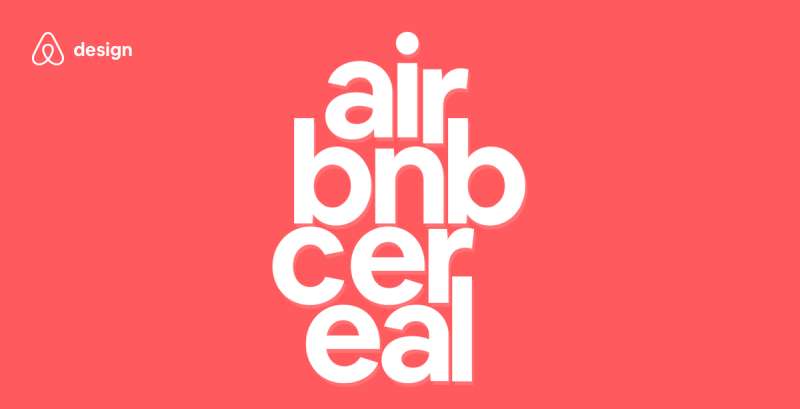
Ah, die perfekte Schüssel ‚Cereal‘. Diese freundliche, unauffällige Schriftart ist das, wovon Airbnb begeistert ist und was sie mit ganzem Herzen angenommen haben. Es ist die Schrift, die Sie sehen, egal ob Sie eine gemütliche Hütte im Wald oder ein schickes Stadtapartment buchen.
Es ist diese geometrische serifenlose Schriftart, die der Airbnb-Plattform einen menschlichen Touch verleiht, und sie wurde so gestaltet, dass sie genauso einladend ist wie die auf der Seite gelisteten Häuser.
Entstehung von Cereal
Wer hat diese wunderschöne Schüssel Cereal kreiert? Es ist das Brainchild des hauseigenen Designteams von Airbnb, mit ein wenig Hilfe von ihren Freunden bei Dalton Maag, der in London ansässigen Schriftgießerei.
Die Zusammenarbeit hat eine Schriftart hervorgebracht, die sowohl modern als auch freundlich ist, genau wie die Marke von Airbnb. Einfache, saubere geometrische Formen sind die Bausteine, mit genau dem richtigen Hauch von Rundheit, um sie zugänglich zu machen.
Die Schönheit von Cereal
Die Cereal-Schriftart ist nicht nur ein hübsches Gesicht. Sie hat auch funktional einiges zu bieten. Sie kommt in sechs verschiedenen Gewichtsvarianten, wodurch sie ziemlich vielseitig ist.
Sie können sie nutzen, um hervorzuheben, zu flüstern, zu schreien – alles mit einer konsistenten Stimme. Und die Skalierbarkeit? Oh, sie meistert es wie ein Champion. Egal in welcher Größe, Cereal behält ihre Integrität.
Alternativen zur Airbnb-Schriftart
Wenn Cereal nicht ganz Ihr Fall ist oder Sie nach etwas anderem für Ihre eigene Marke suchen, keine Sorge. Es gibt ein Buffet an alternativen Schriften da draußen.
Roboto
Roboto ist wie der ältere, weisere Cousin von Cereal. Entwickelt von Google, ist es eine weitere geometrische serifenlose Schriftart, die sauber, modern und super adaptierbar ist. Sie hat eine noch größere Bandbreite an Gewichten und Stilen. Sie ist ziemlich populär und Sie haben sie wahrscheinlich schon gesehen.
Proxima Nova
Nächster im Menü ist Proxima Nova. Stellen Sie sich Cereal vor, aber mit etwas mehr Kante und weniger Rundheit. Sie ist professionell, aber nicht zu steif, freundlich, aber nicht übermäßig. Sie ist ein wunderbarer Mix, der in vielen Kontexten gut funktioniert.
Die Wirkung von Typografie auf Branding
Sie könnten denken, dass Schriftarten nur Schriftarten sind, aber in der Welt des Designs sind sie so viel mehr. Sie können die Identität einer Marke definieren und beeinflussen, wie Nutzer die Marke wahrnehmen.
Die Macht von Schriftarten
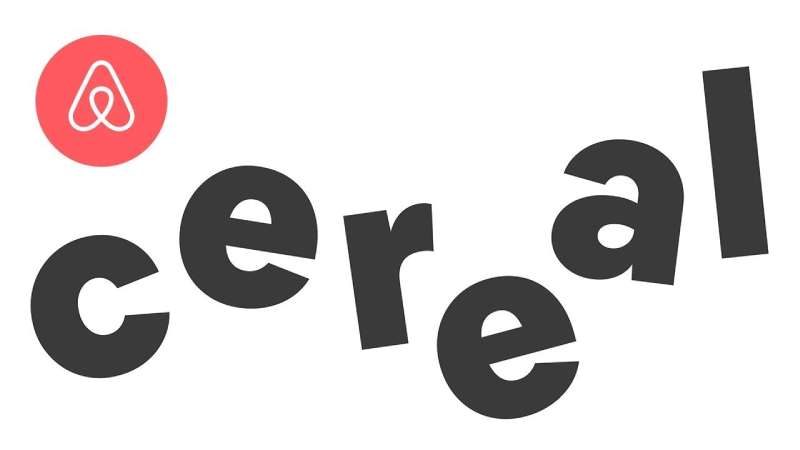
Schriftarten sind wie die Kleidung, die Worte tragen. Sie können Worte ernst, lässig, lustig oder raffiniert erscheinen lassen. Wenn eine Marke wie Airbnb eine Schriftart wählt, macht sie eine Aussage über ihre Identität. Und mit Cereal sagt Airbnb, dass es freundlich, modern und einladend ist.
Konsistenz ist der Schlüssel
So wie Sie kein nicht zusammenpassendes Outfit tragen würden, müssen Marken sicherstellen, dass ihre Typografie konsistent ist. Hierbei ist eine benutzerdefinierte Schriftart von Vorteil. Mit Cereal kann Airbnb sicherstellen, dass jedes Wort, das es spricht, konsistent mit seiner Marke ist, egal wo es erscheint.
FAQ zur Airbnb-Schriftart
Wie heißt die Airbnb-Schriftart?
Die Schrift, die die Airbnb-Seite in Eleganz hüllt? Sie heißt Cereal. Eine schicke, maßgeschneiderte serifenlose Schönheit. Sie sticht hervor, nicht wahr?
Maßgeschneidert, um Zuschauer mit ihrer einzigartigen visuellen Identität zu fesseln, verkörpert Cereal die Wärme und Gastfreundschaft, die Airbnb durch sein Branding vermitteln möchte.
Warum hat Airbnb eine benutzerdefinierte Schriftart erstellt?
Warum sich mit dem Von-der-Stange begnügen, wenn man maßgeschneidert gehen kann? Das hat sich auch Airbnb gedacht.
Die Erstellung von Cereal diente dazu, eine unverwechselbare visuelle Ausdrucksweise zu treffen; ein Schriftstil, der nahtlos mit der Typografie der Markenidentität resoniert und das Benutzererlebnisdesign mit jener heimeligen Atmosphäre verstärkt, die Airbnb liebt.
Kann ich die Airbnb-Schrift herunterladen?
Halten Sie die Pferde, mein Freund. Cereal ist nicht zu haben. Es ist Airbnbs eigenes Spielzeug, nicht für die öffentliche Nutzung lizenziert.
Respektieren Sie ihr geistiges Eigentum, finden Sie vielleicht Alternativen mit ähnlicher Lesbarkeit der Schriftart oder Stimmung, aber denken Sie daran, keine zwei Schriften tragen dieselbe Seele.
Wie beeinflusst die Airbnb-Schrift das Branding?
Schriftarten flüstern das Wesen einer Marke in Ihr Unterbewusstsein. Mit Cereal sprechen die Branding-Schriften von Airbnb in entspannten, aber raffinierten Tönen.
Es ist alles Teil ihres Corporate Branding-Werkzeugs – dafür zu sorgen, dass Sie bei jeder Online-Interaktion diese Airbnb-Umarmung spüren.
Ist die Airbnb-Schrift als zugänglich angesehen?
Zugänglichkeit ist der Schlüssel, und ja, Cereal erfüllt dieses Kriterium. Ihre klaren Formen und ausreichenden Abstände erhöhen die Lesbarkeit der Schriftart, sodass auch Personen mit Sehbeeinträchtigungen problemlos an der Airbnb-Party teilnehmen können. Es ist Benutzerfreundlichkeit, die in den Stoff der digitalen Typografie eingewoben ist.
Wie verbessert die Airbnb-Schrift das Benutzererlebnis?
Cereal wurde frisch gebacken, mit dem Design des Benutzererlebnisses im Sinn.
Ihr einheitliches Aussehen über digitale Plattformen hinweg bedeutet keine störenden Änderungen für die Augen – einfach reibungsloses Navigieren von Bildschirm zu Bildschirm, was die Usability der Plattform erhöht und die Stimme der Marke fest im Einklang hält.
Um welche Art von Schriftart handelt es sich bei der Airbnb-Schrift?
Cereal gehört zur Familie der serifenlosen Schriftarten – keine zusätzlichen Schnörkel an den Buchstaben. Schlank. Modern. Passt hervorragend zu digitalen Displays.
Eine bevorzugte Wahl für klare digitale Branding-Assets, halten serifenlose Schriften wie Cereal alles klar und zeitgemäß.
Ist die Airbnb-Schrift einzigartig für Airbnb?
Einzigartig wie Schneeflocken in ihrem Design, sind benutzerdefinierte Schriftarten wie Cereal seltene Vögel.
Die Schriftart von Airbnb mit ihrer deutlichen und unabhängigen Existenz ist nicht nur einzigartig – sie ist eine SEO-Einheit ihrer selbst innerhalb des Designsystems. Sie ist Airbnbs Unterschrift in typografischer Form.
Wie hat Airbnb sich für diesen speziellen Schriftstil entschieden?
Es war keine Würfelwurfentscheidung. Cereal auszuwählen, war durchdacht, strategisch. Man wollte etwas, was die Markenidentität widerspiegelt.
Eine Schrift, gezüchtet für Lesbarkeit, Flexibilität über Medien hinweg, etwas, das ‚Airbnb‘ sang, ohne ein Wort zu sagen. Es ist ein Game-Changer in der visuellen Identität.
Welche Art von Schrifttrends setzt die Airbnb-Schrift?
Airbnb hat mit Cereal etwas vor – sie setzt Typografietrends, indem sie Wärme mit Modernität verbindet. Sie beweist, dass benutzerdefinierte Schriftarten als Branding-Assets eine firmeneigene digitale Anwesenheit neu definieren können.
Beobachten Sie, wie mehr Marken auf diesen Designtrend-Zug aufspringen und ihre eigenen typografischen Signaturen suchen.
Fazit
Wir sind durch die Gassen der digitalen Typografie gewandert und haben die vielfältigen Geschichten aufgedeckt, die innerhalb der Airbnb-Schriftart verwoben sind. Cereal steht nicht nur als eine Serie wohlgestalteter Linien und Kurven, sondern als Leuchtfeuer der Markenidentität von Airbnb. Es ist klar.
- Die Serifenlosigkeit der Schrift strahlt nicht nur ästhetische Anziehungskraft aus; sie ist der Grundstein des Benutzererlebnis-Designs.
- Die bewusste Wahl dieser Schriftart spiegelt Airbnbs Philosophie wider – Einfachheit, Inklusivität und Wiedererkennung.
In jeder Hinsicht ist Cereal eine Schrift, die spricht, ohne zu schreien, den Markengeist von Airbnb unterstützt und sich mühelos in die digitalen Plattformen einfügt. Ihre subtile Kraft, eine Plattform zu gestalten, die sich wie Zuhause anfühlt, kann nicht unterschätzt werden. Sie setzt einen Designtrend und kündigt eine Zukunft an, in der benutzerdefinierte Schriftarten vielleicht zur Norm werden – ebenso integraler Bestandteil einer Marke wie die angebotenen Dienstleistungen.
Sollte dies eine Neubewertung Ihrer eigenen digitalen Präsenz inspirieren? Nun, die Fallstudie von Cereal legt nahe, dass es den Gedanken wert ist.